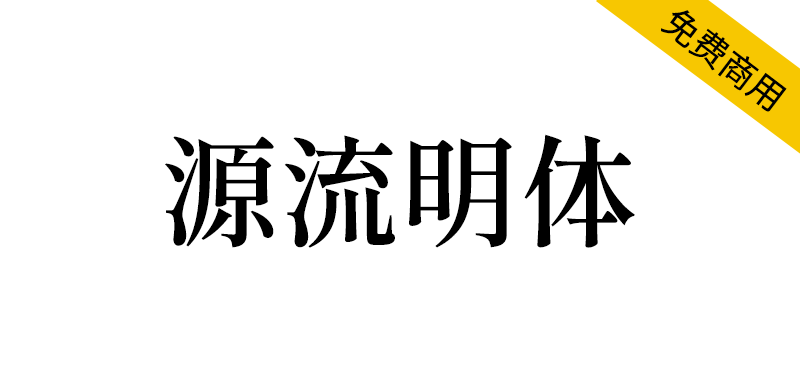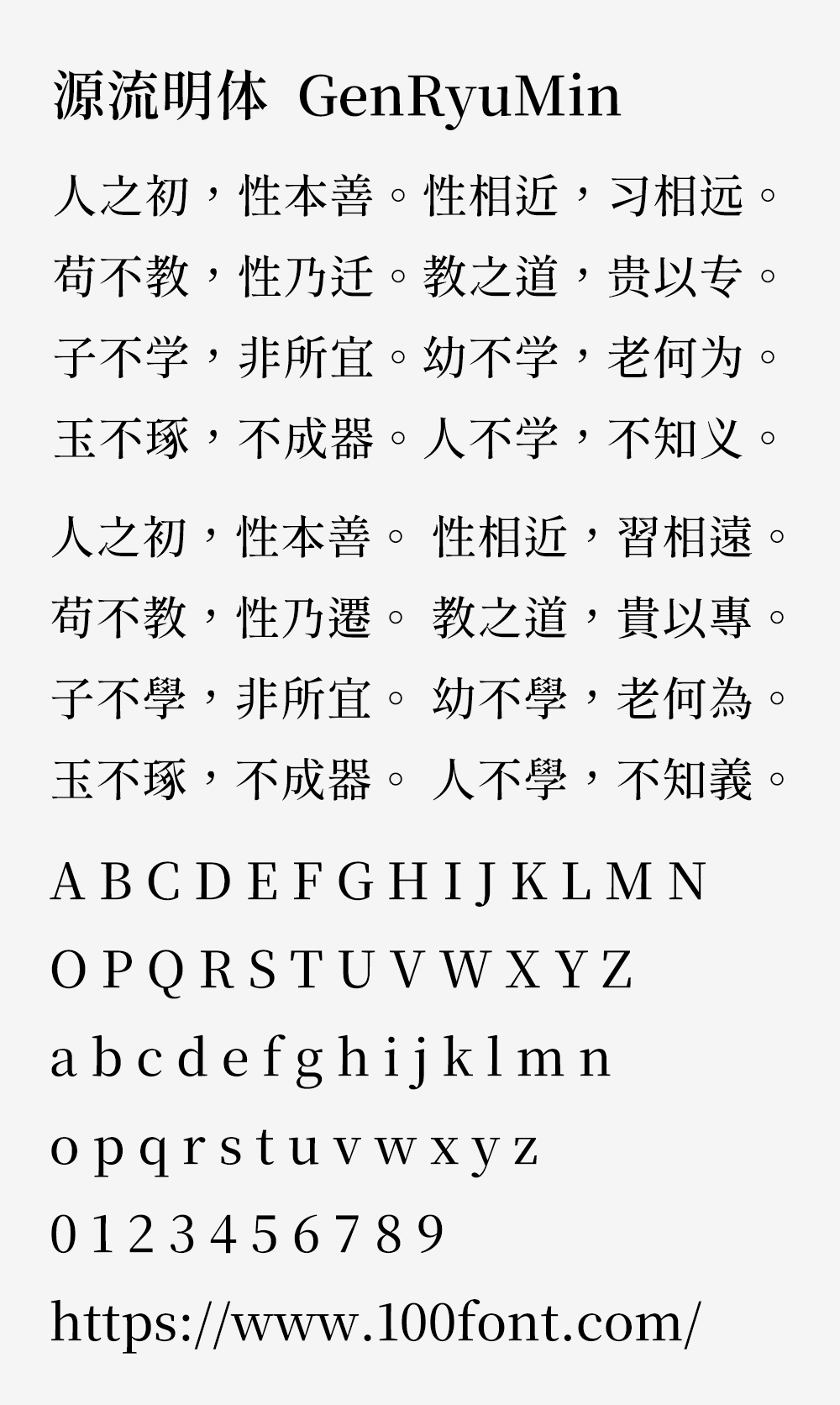
源流明体是基于思源宋体的而改造的开放原始码中文字体。汉字宽度稍微压缩,显得比原始的思源宋体要稍微瘦长。并且在横笔的起笔与竖笔的起笔、收笔处,全都加上粗细变化。仿佛重现铅字的压印感,文字较有文学感、人文气息。
Note. 请注意以上改造乃以计算机程序自动进行,未进行任何人工处理,在部分笔画复杂文字可能会有笔画不太一致的情况。
7个字重,完全重制思源宋体原来所有7个字重,无论极粗或极细,都能使用源流明体的古典风格!